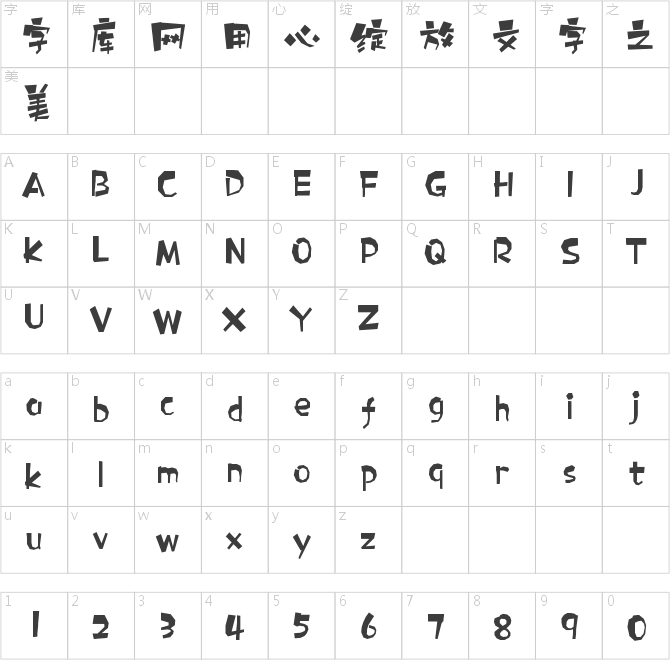
壹心
字形特點(diǎn):
方正中帶有動(dòng)感,棱角分明,以方折構(gòu)建起字體的框架,活潑生動(dòng),辨識(shí)度高;
壹心夏日體字體yixinxiariti字庫是一款讓人賞心悅目、百看不厭的中文字體,適合各類廣告和產(chǎn)品包裝設(shè)計(jì)應(yīng)用,字體大小7.24MB,格式為ttf字體,上傳用戶是gagilang,作者/版權(quán)方為壹心字庫